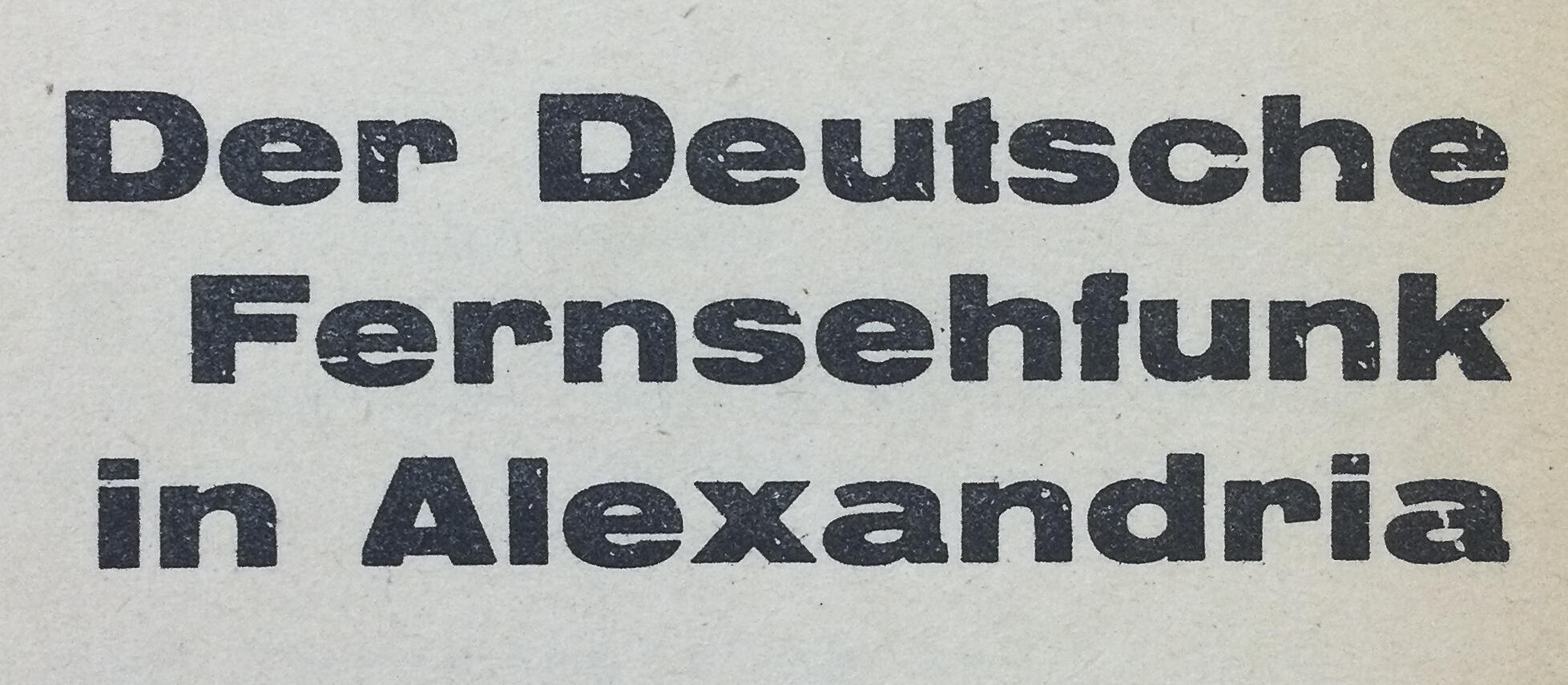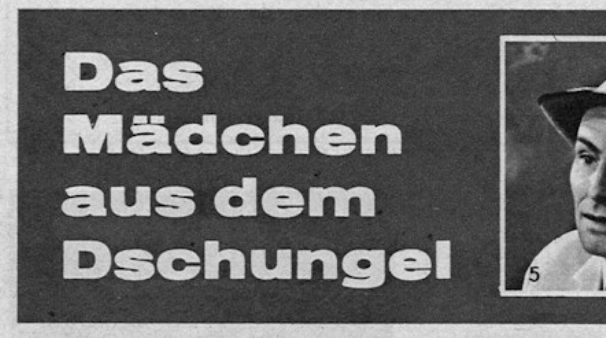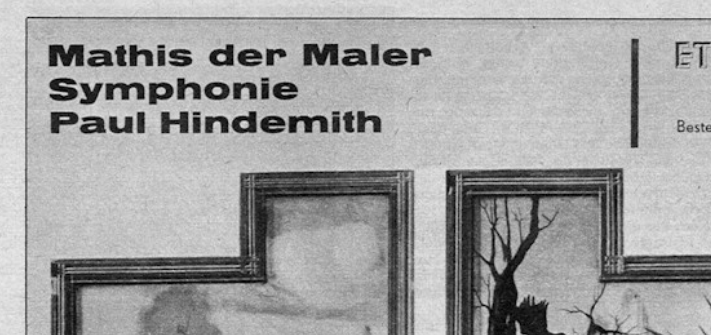
Moderne Schriftart aus DDR-Zeitschrift 1964 gesucht
In der FF dabei von 1964 habe ich oft diese Schrift gefunden. Ebenso wurde sie auf Schallplattencovern verwendet. Ich hab an Akzidenz-Grotesk gedacht.